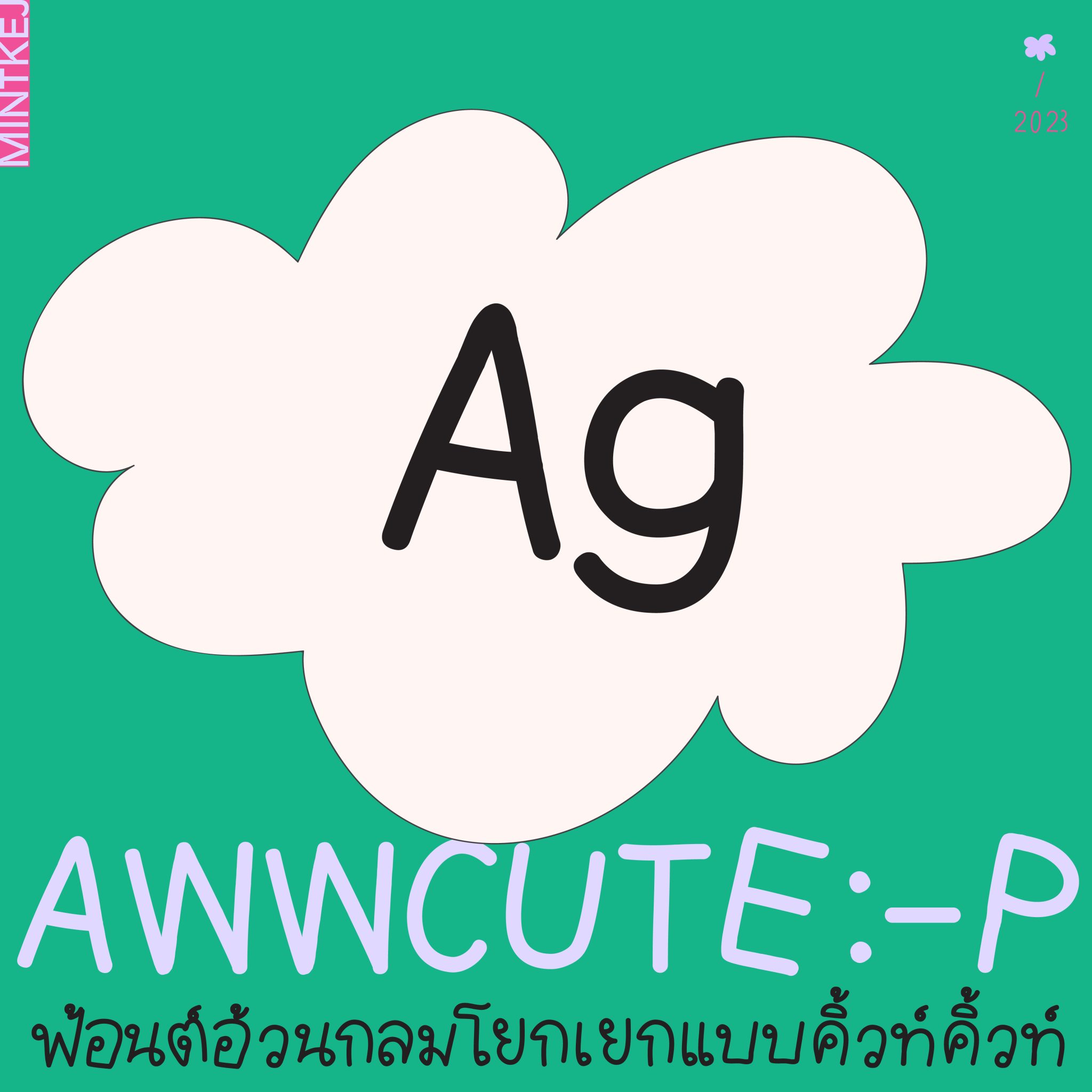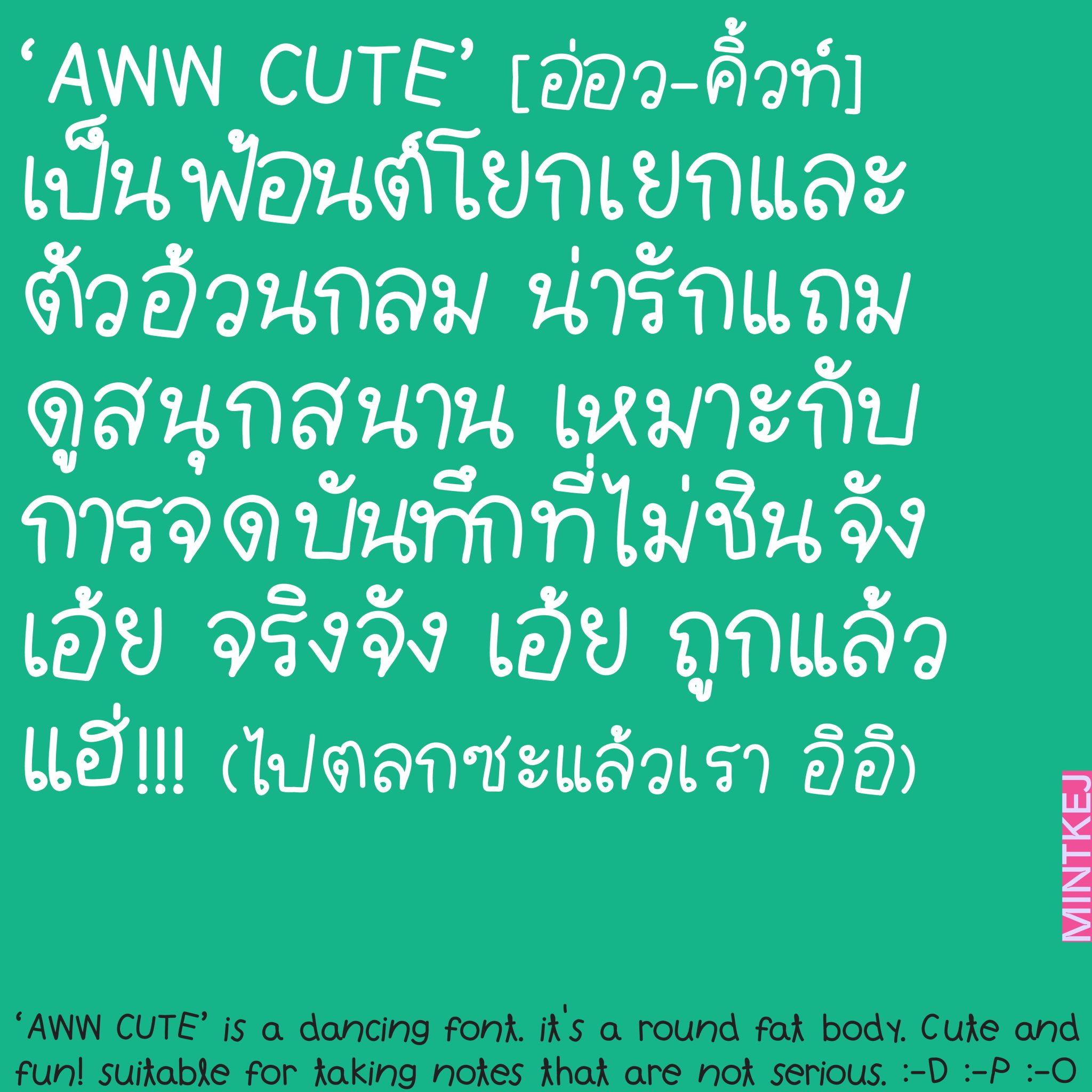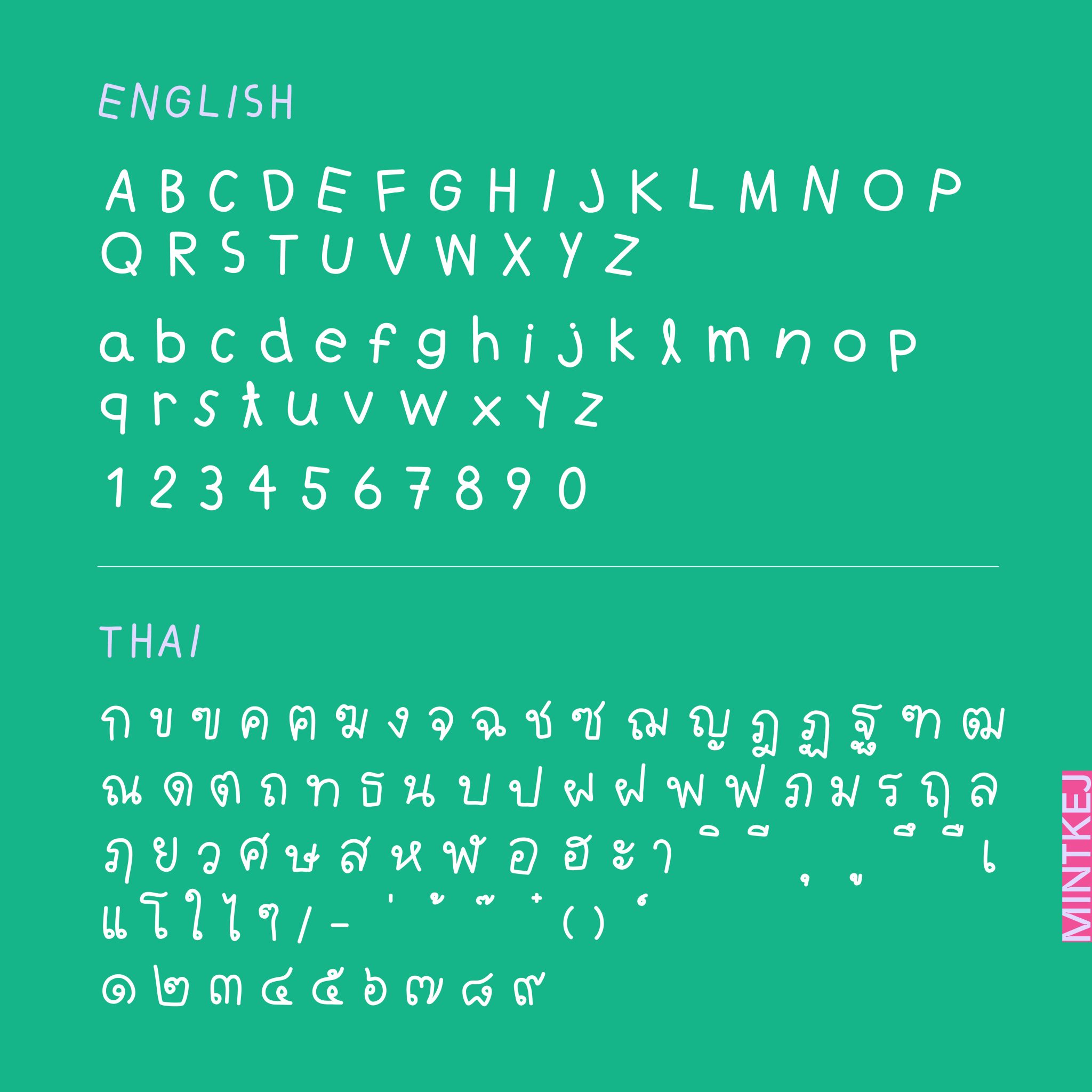
MINTKEJ | FONT (awwcute)
MINTKEJ – AWW CUTE
อ่อว-คิ้วท์ เป็นฟ้อนต์โยกเยกและตัวอ้วนกลม น่ารักแถมดูสนุกสนาน เหมาะกับการจดบันทึกที่ไม่จริงจังมาก
สามารถใช้กับหัวเรื่องหรือเนื้อหาก็ได้ แต่ถ้ารู้สึกว่าแคบไปสามารถปรับระยะห่างตามใจชอบได้เลยค่ะ 😀